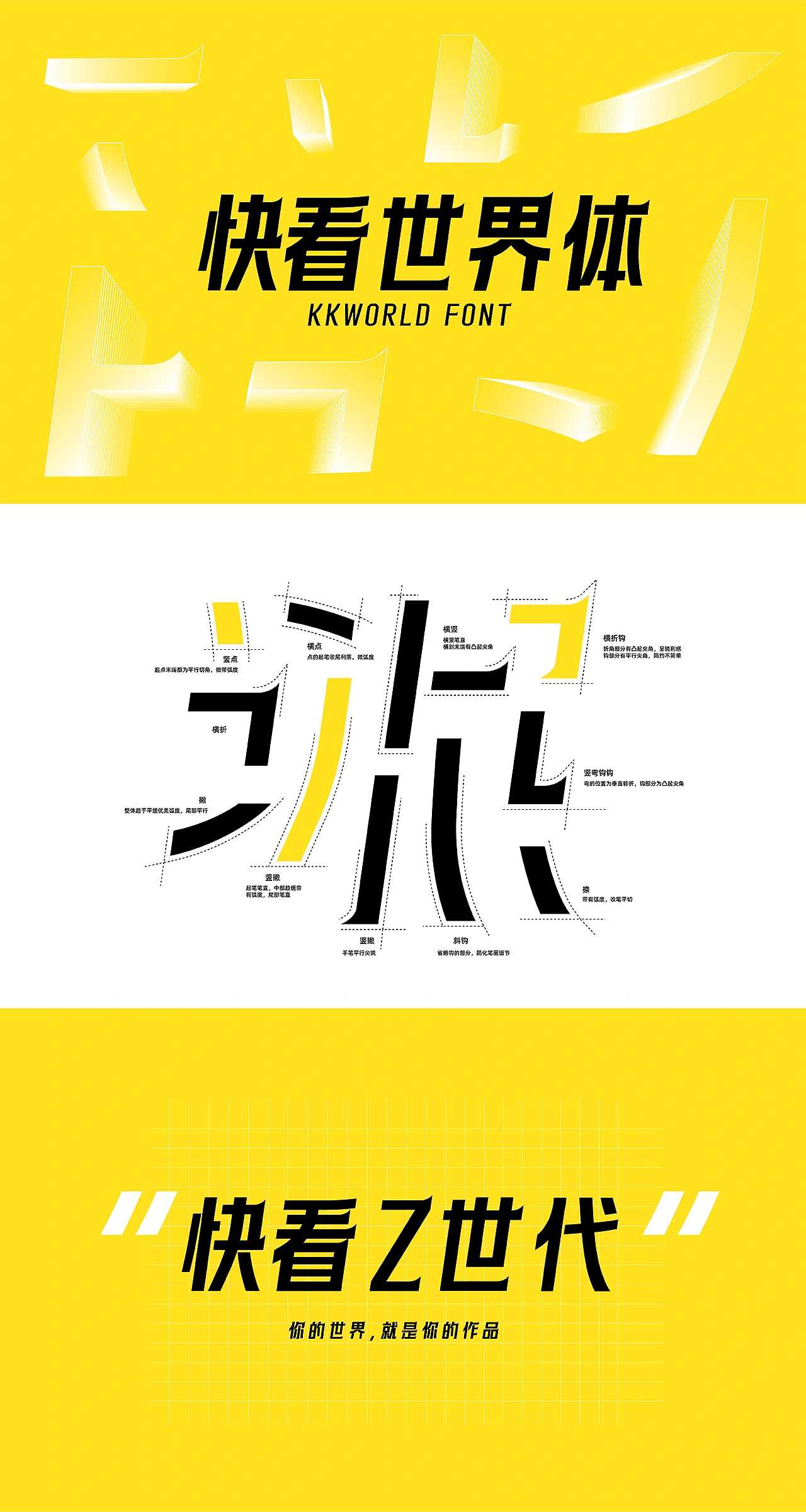
字体名称: 快看世界体
快看世界体
快看世界体介绍
这款字是我第一款从设计-封装-测试全部自己完成的字库
快看世界体由快看KKDC出品,字体设计以漫画中的对话框元素为起点,
融入快看ACGN文化,年轻潮流,大胆有态度。
字体特点末端尖角,中宫外扩、字面瘦长、倾斜8度;包含3605个字。
现应用于快看品牌营销、漫展、内部企业文化宣传、客户端等场景。免费授权全社会使用(包括商用)